안병국의 웹타이포그래피 – 사용자의 시선 유도를 위한 전략
때때로 디자인으로서의 타이포그래피 성격은 무시하고 전달자의 목소리만 드높인 웹사이트를 보게 된다. 타이포로 인해 전체 디자인이 흐트러지는 ‘사고’도 종종 목격한다. 이번 글에서는 웹타이포그피를 구현함에 있어 심미성을 잃지 않으면서 동시에 메시지를 효과적으로 전달하는 다양한 사례들을 살펴보고 몇 가지 법칙을 제시하고자 한다.
모델 시선 방향에 맞춰 배치하기
LS산전과 현대카드 GE파트너 사이트는 모델의 시선 각도에 따라 타이틀을 배치한 예다. 주로 키-타이틀(Key Title)을 배치할 때 유용하게 쓰는 방법이다. 이는 비주얼에서 가장 핵심이 되는 모델을 응시한 뒤 자연스럽게 모델이 바라보는 방향에 따라 시선을 이동하는 사용자의 습관이나 심리를 이용하는 것이다. 자연스럽게 텍스트를 읽도록 하고 다음 컨텐츠로 쉽게 유도할 수 있다는 장점이 있다.
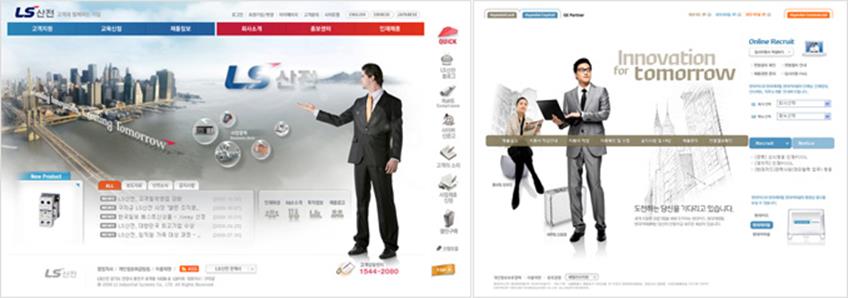
LS산전과 현대카드 GE 파트너 사이트
모델 시선을 이용해 타이포를 배치한 경우 타이포의 가로 폭이 넓으면 면으로 인식되기 보다는 선(line)으로 인식되기 쉽다. 그렇기 때문에 전체적인 비주얼 구도를 깨뜨리고 가독성을 저해할 위험과 가능성이 높다. 또한 가로 폭이 넓은 타이틀을 억지로 이미지 구도에 맞추다 보면 선으로 닫힌 비주얼이 될 수 있어 공간을 충분히 고려해 디자인 해야 한다.
아래 LS산전 사이트에서 타이틀의 공간 배치를 살펴보면 잘된 부분과 그렇지 않은 부분을 확인할 수 있다. 모델의 시선 방향과 높이에 맞춰 배치한 CI는 입체감과 집중도를 높여준 반면, 화면 왼편에 배치된 메인 타이틀은 글자 수가 많고 가로 폭이 넓어 억지로 이미지 구도에 맞추고 있다. 가독성을 떨어뜨리고 인위적으로 느껴진다.
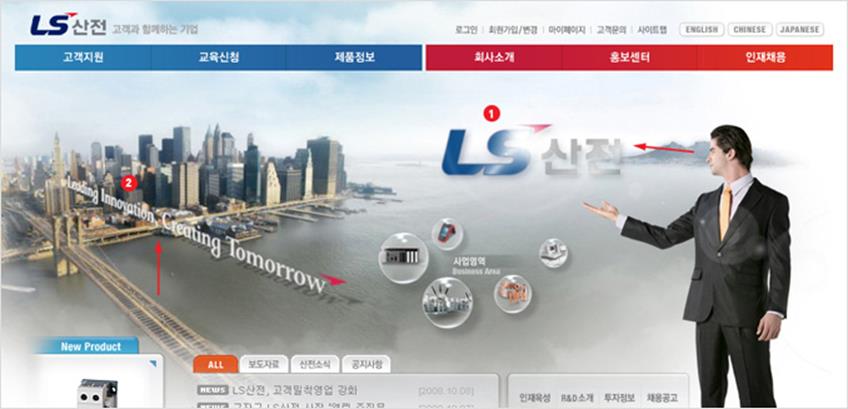
LS산전 웹사이트
이처럼 모델의 시선 또는 공간에서의 타이포 배치에 있어서 전체 비주얼의 구도와 조화를 고려한 디자인이 이루어져야 디자인의 기획 의도를 효과적으로 전달할 수 있다. 모델을 통해 사용자의 시선을 유도하는데 성공했다면 다음 비주얼 및 컨텐츠로의 연결을 어떻게 가져가야 효과적인지, 어떻게 해야 사용자의 시각적 피로감을 최소화할 수 있는지 등을 디자인적으로 고민하는 노력이 있어야 한다.
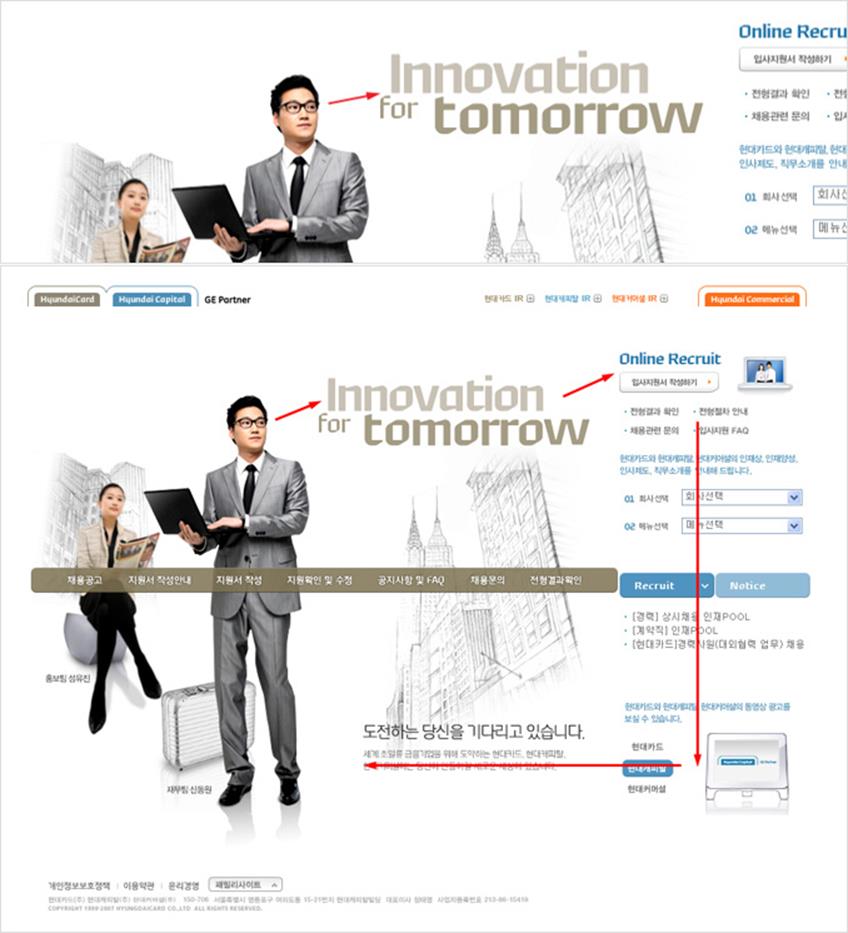
현대카드 GE 파트너 사이트에서 비주얼존을 살펴보면 배경이 되는 건물들이 메인 모델에 비해 스케치톤으로 약하게 처리 되어 있다. 그렇기 때문에 이 사이트를 방문한 사용자는 다른 비주얼 요소들로 인해 모델에 집중할 때 방해를 받지 않는다. 자연스럽게 모델의 시선 또는 동세에 따라 시선을 가져갈 수 있다.
특히, 메인 타이틀을 확인한 방문자는 자연스럽게 배경 이미지보다는 오른쪽에 위치한 컨텐츠존으로 시선을 이동하게 된다. 이는 배경이 되는 건물 그림이 전체 이미지 구도를 좌우할 수 있을 만큼 강도가 높지 않기 때문이다. 즉 배경이 되는 건물보다는 컬러와 밀도로 시각적 강도를 높인 오른쪽 컨텐츠존으로 사용자 시선을 유도함으로써 사용자가 전체 내용을 파악할 수 있도록 디자인되었기 때문이다.
모델의 운동방향에 맞춰 배치하기
정지된 이미지라 해도 비주얼에 등장하는 디자인 요소들에서 움직임에 형태가 있거나 특정 동선의 비주얼을 강조하고자 할 때 타이틀도 전체 느낌에 맞춰 강조하는 경우가 많다. 사용자 시선이 타이틀 흐름에 많이 좌우되기 때문이다. 아래 사이트는 모델의 운동 방향에 맞춰 타이틀을 배치하고 움직임에 무게감을 주거나 사실적인 입체감을 느낄 수 있도록 디자인된 좋은 사례다.
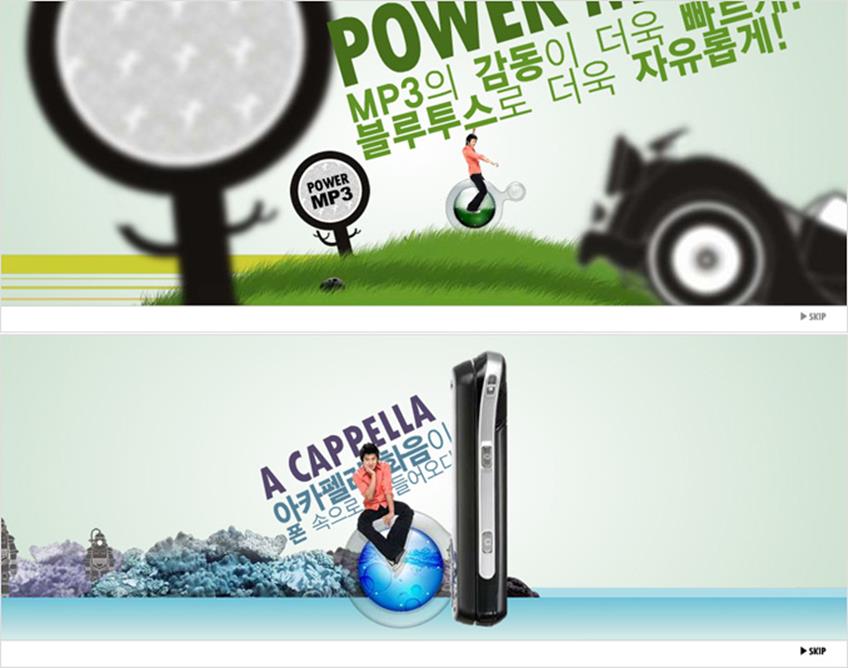
위 사이트에서 처음부터 타이포를 배제했거나 수평으로 배치했다면 모델의 움직임은 거의 느껴지지 않을 정도로 큰 비중으로 전달되지 않았을 것이다. 하지만 타이포 배치 하나만으로 불안정하게 느껴질 수 있는 모델의 움직임이 훨씬 자연스럽고 안정감 있게 표현되었고, 타이포가 화면에서 전체 무게를 지탱해 주는 무게 중심축으로서의 역할도 병행하고 있다. 결국 위 사이트에 사용된 타이틀이 비주얼의 동세, 즉 운동 방향에 맞춰 배치됨으로써 타이틀과 비주얼이 개별적으로 독립된 형태가 아닌 하나의 비주얼을 구성해 화면의 입체감을 높였다.
화면 구도에 맞춰 배치하기
비주얼을 강조하고 카피를 보조적인 하나의 수단으로 활용하고 싶을 때 카피를 비주얼의 한 요소로 사용하곤 한다. 화면 전체가 하나의 비주얼로 인식될 수 있고 사이트 방문자는 비주얼에서 전달 받은 시각적 느낌 그대로 사이트를 인지하게 된다. 하지만 비주얼을 중시하는 영화 사이트나 프로모션 사이트 외에 텍스트 분량이 많고 다양한 컨텐츠를 노출해야 하는 사이트에서는 비주얼에 시선이 집중되기 때문에 정보를 확인하는 과정에서 어려움이 따를 수 있다.
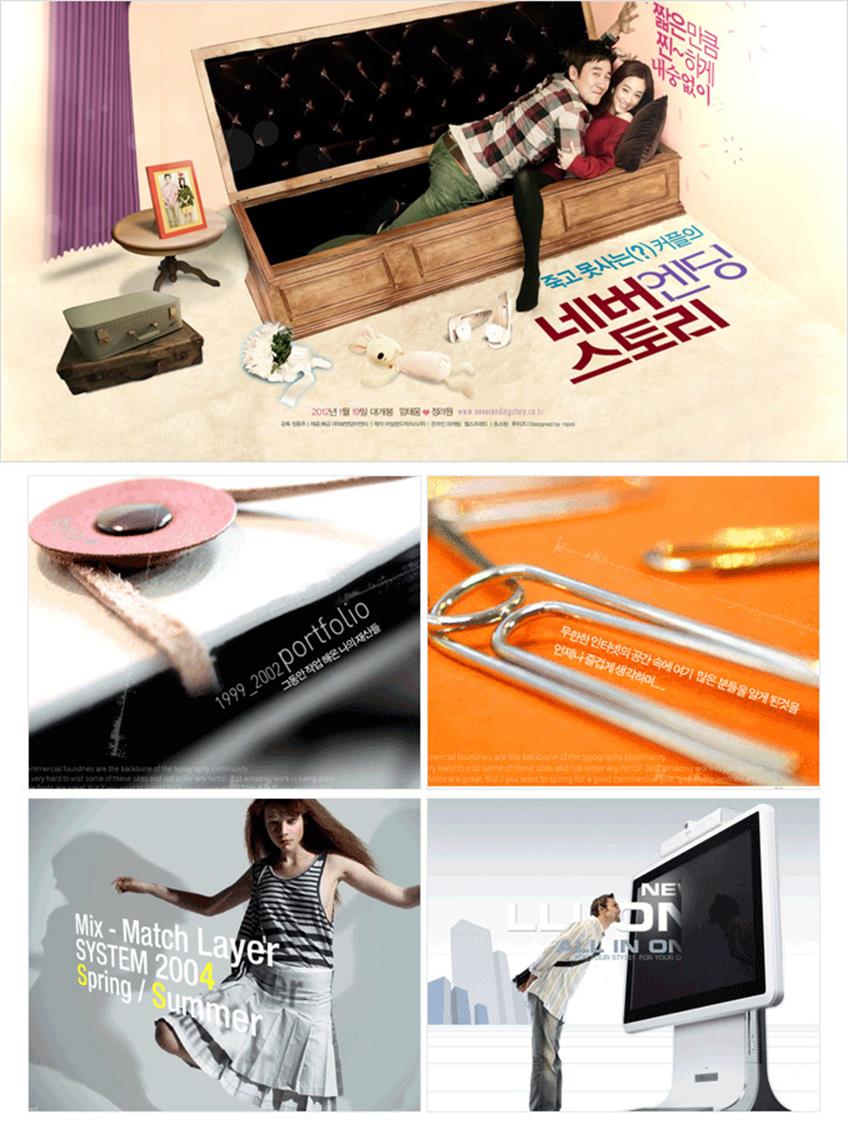
즉, 수직 수평에 따른 분할에 익숙한 사이트 방문자는 큰 타이틀이 아니고서는 많은 양의 텍스트 정보를 불편한 구도 속에서 찾아 읽는 과정을 꺼려할 수 있다. 방문자들에게 외면 받는 사이트가 될 가능성이 높다. 정보 제공과 이미지 전달 모두를 놓칠 수 있는 위험성도 크다.
좌뇌와 우뇌
웹사이트 디자인을 전반적으로 살펴보면 왼쪽에 비주얼이 위치하고 오른쪽에 타이틀 문구나 카피가 위치하는 경우가 많다. 이는 디자이너들이 무의식적으로 웹사이트를 디자인 하면서 이를 가장 안정된 구조로 느끼기 때문이다. 하지만 이는 결코 느낌상의 문제는 아니다. 사람의 시각은 우뇌와 좌뇌의 영향을 받아 사물을 인지하고 분석한다. 왼쪽에 그림이 위치하고 오른쪽에 타이틀이 위치함으로써 안정감을 느끼게 되는 이유는 우측에 놓인 정보를 파악하는데 언어능력과 수리능력을 담당하는 좌뇌가 관여하기 때문이고 좌측에 위치한 정보는 시공간 및, 감성적 능력을 관여하는 우뇌가 관여하기 때문이다.
아래 두 사례를 비교해보자. 아이오페 사이트에서 모델은 왼쪽에, 텍스트는 오른쪽에 배치해 안정감을 주고 있다. 반면 모델 이미지와 텍스트 위치가 반대인 케라시스 사이트에서는 왼쪽 사이트보다 다소 안정감은 떨어져 보인다. 하지만 역동적인 느낌을 전달하고 있다. 또한, 한 사이트에서는 단아하고 정결한 헤어스타일의 모델 이미지를, 다른 하나에서는 역동적인 웨이브 형태의 헤어스타일이 강조된 모델 이미지를 사용했다. 두 사이트 모두 좌뇌와 우뇌의 특징을 효과적으로 응용한 디자인이라 할 수 있다.
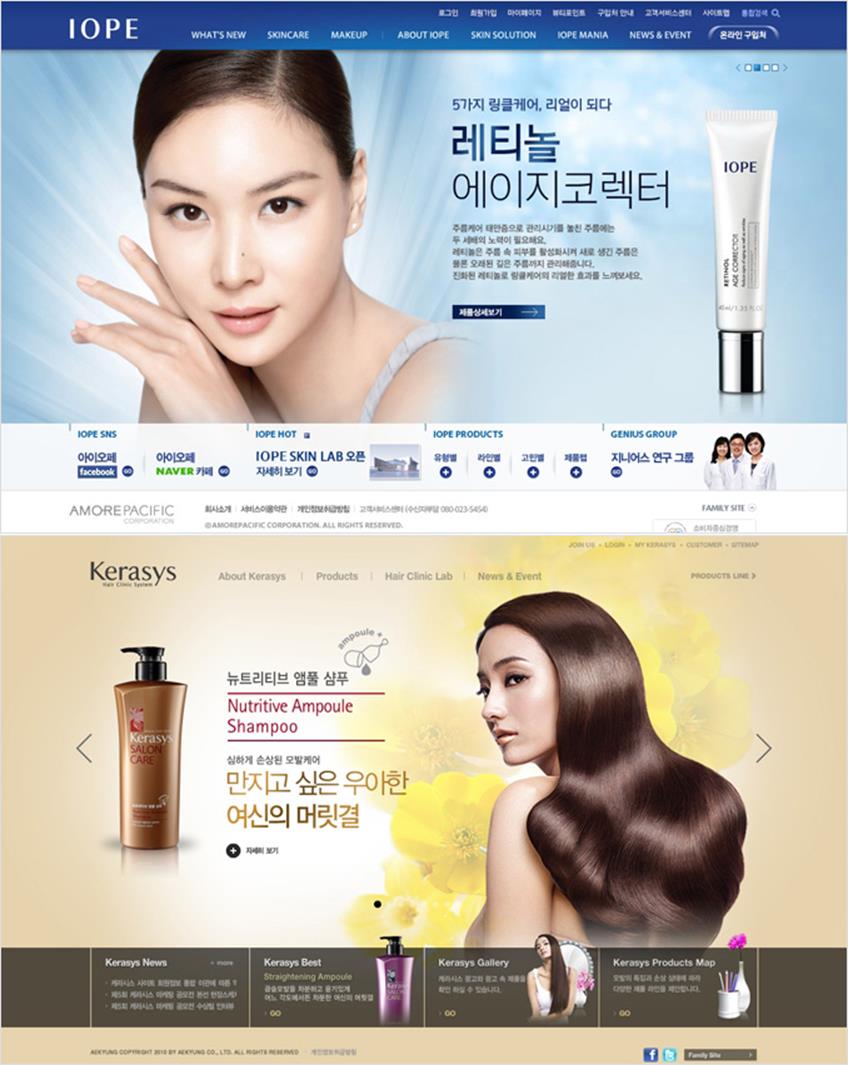
마찬가지로 자동차 사이트에서도 세단과 스포츠카를 비교해볼 수 있다. 세단을 광고하는 사이트에서는 역동성보다는 고급스러움과 안정성을 강조해야 한다. 그렇기 때문에 자동차 방향이 왼쪽에서 오른쪽으로 향해 있다. 반면, 스포츠카는 역동적인 느낌을 전달하기 위해 자동차 이미지를 세단과는 다른 방향으로 배치한 것을 확인할 수 있다.
지금까지 모델 이미지의 시선, 운동 방향, 화면 구도, 좌뇌와 우뇌의 특성 등을 고려해 이미지와 텍스트를 배치하고 타이포그래피를 응용하는 방법에 대해 알아보았다. 이처럼 웹디자인에서의 타이포그래피는 단순히 내용을 전달하고 화면을 꾸미기 위한 디자인적인 요소가 아니다. 그보다는 소비자의 심리를 자극해 보다 효과적인 마케팅이 가능하도록 도와주는 굉장히 중요한 기능과 역할을 수행한다. 앞서 소개한 몇 가지 사례를 바탕으로 보다 다양한 전략의 웹타이포그래피를 응용해보길 바란다.